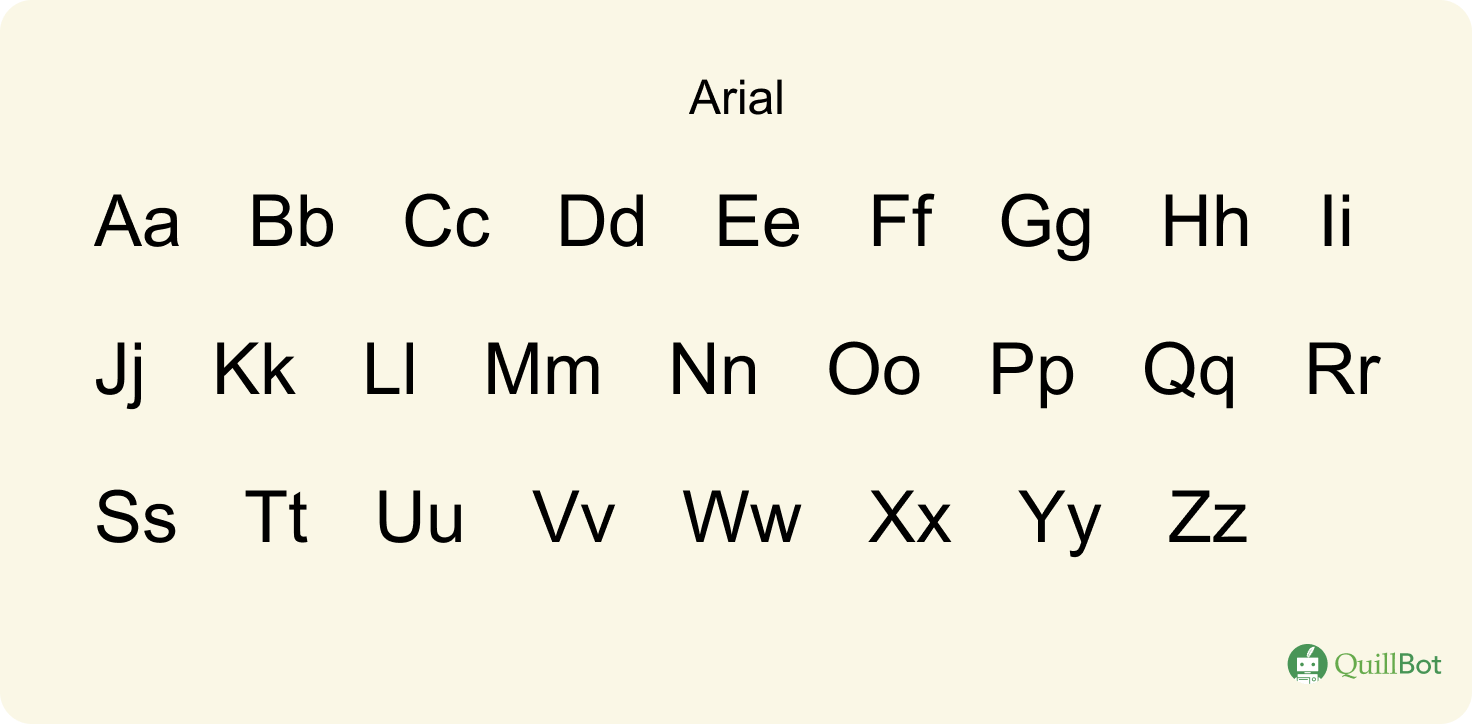
Arial | Une police made in Microsoft
Tout graphiste expérimenté vous le dira : trouver LA bonne police d’écriture requiert un savoir-faire et un sens esthétique qui ne s’inventent pas.
Loin de relever du détail ou de la simple coquetterie, une typographie peut influencer considérablement la lisibilité et l’accessibilité du message qu’elle porte. Elle est également à même d’appuyer la ligne éditoriale d’une marque, en fonction de son identité et de sa réputation auprès du grand public.
Fantaisistes ou fonctionnelles, minces ou grasses, rondes ou linéaires, les polices de caractères peuvent prendre de nombreuses formes…
Parmi les grands classiques du genre, intégrés d’office sur tous les logiciels de traitement de texte par défaut ou presque, on retrouve bien sûr Arial.
- Année de création : 1982
- Pays de création : États-Unis
- Créateurs : Robin Nicholas et Patricia Saunders (typographes chez Monotype Imaging)
- Type de police : Linéale
- Type d’empattement : Sans empattement (sans serif en anglais)
- Classification Thibaudeau : Antique
- Popularité : ++ (très utilisée car présente par défaut sur Windows, mais peu appréciée des graphistes)
- Image véhiculée : Fonctionnelle, universelle, basique, voire banale.
- Point d’attention particulier :
- Initialement pensée comme un substitut low-cost à Helvetica.
- Optimisée pour l’impression laser à basse résolution.
Arial est l’une des plus célèbres, si ce n’est la plus connue, des polices d’écriture. Paramétrée par défaut sur de nombreux traitements de texte, parmi lesquels Google Docs, elle est toujours utilisée en masse… malgré le désamour croissant des designers à son égard.
Police Arial : histoire et développement
N’ayons pas peur des mots : Arial, c’est d’abord une affaire d’oursins dans les poches…
Au début des années 1980, la police Helvetica est au sommet de sa gloire. Elle ne doit pas seulement sa popularité d’alors à ses lignes nettes et épurées qui la rendent idéale à des fins diverses, mais aussi parce que son rendu à l’impression est idéal.
De ce fait, les graphistes qui la choisissent peuvent être sûrs que le résultat matériel sera à la hauteur de la maquette numérique, sans crénages ratés ou autres déconvenues à même de ruiner des semaines de travail.
Au moment de mettre au point ses premiers systèmes Windows, Microsoft lorgnait évidemment sur ce joyau de la typographie fonctionnelle, mais un problème s’est rapidement posé : Helvetica était sous licence, et il fallait payer un tribut conséquent à ses ayants droit pour l’utiliser.
Qu’à cela ne tienne, Arial a été pensée puis dessinée comme un substitut d’Helvetica.
Même largeur de lettres, mêmes césures… La ressemblance est telle qu’on ne voit pas très bien la différence entre les deux au premier coup d’œil.
De cette manière, les traitements de texte affichaient correctement les documents pensés à l’origine pour Helvetica… à moindre coût.
L’ironie, dans l’histoire, c’est que le nom d’Arial est aujourd’hui plus connu que celui d’Helvetica, eu égard à la popularité de Windows et au raz-de-marée informatique survenu à partir de la fin des années 1990 dans le monde occidental.
Arial, un classique parmi les classiques
Arial (ainsi que ses variantes Arial Black, Arial Bold, Arial Narrow, Arial Rounded, Arial Light, Arial Medium, etc.) est une police de caractère dite linéale, ou sans empattement.
Et cette caractéristique n’est pas sans conséquence sur la façon dont elle est perçue par les lecteurs, loin de là…
Ce type de police s’oppose aux polices dites avec empattement, distinction que l’on opère selon un critère visuel immédiatement reconnaissable.
- Les polices serif (avec empattement en français) possèdent de petits « pieds », crochets ou traits décoratifs aux extrémités de leurs caractères.
Elles évoquent immédiatement un design classique, sérieux, et confèrent à la communication un caractère institutionnel symbolique d’une certaine autorité.
Elles sont aussi très utilisées dans l’édition et la presse écrite, car jugées plus adaptées à la lecture de textes sur le long court.
Exemples de polices avec empattement : Baskerville, Garamond, Palatino Linotype, Times New Roman…
- À l’inverse, les polices sans serif ne possèdent pas d’empattements. Leurs lignes sont droites et nettes.
Leur aspect est moderne et minimaliste ; leur design épuré, mais accessible.
On les utilise volontiers sur le web en raison de leur lisibilité optimisée pour les écrans et de leur côté « percutant ».
- échanges ou rapports professionnels,
- contenus pédagogiques synthétiques,
- tableaux et formulaires,
- textes courts, destinés en priorité à un lectorat que l’on sait pressé,
- textes présentés et/ou imprimés dans une police de petite taille à des fins minimalistes ou écologiques,
- communications formelles.
À l’inverse, on aura tendance à éviter Arial :
- si l’on recherche une typographie racée, à même de représenter un message fort dès le premier contact visuel,
- pour mettre en page un texte long/de type littéraire,
- afin de se démarquer.